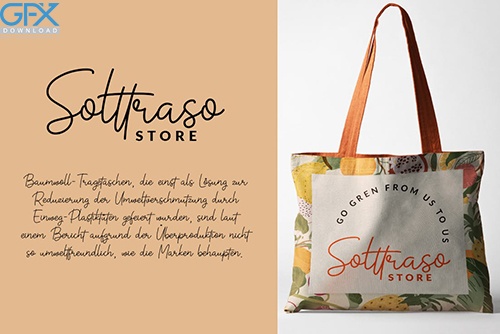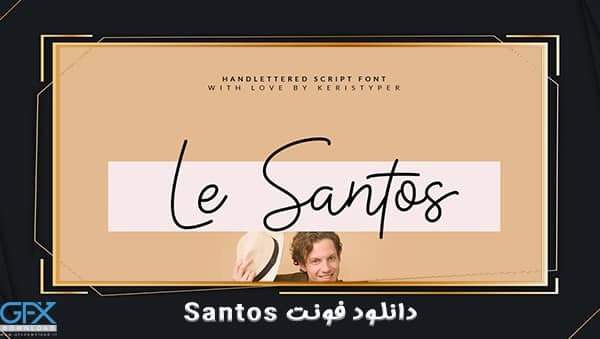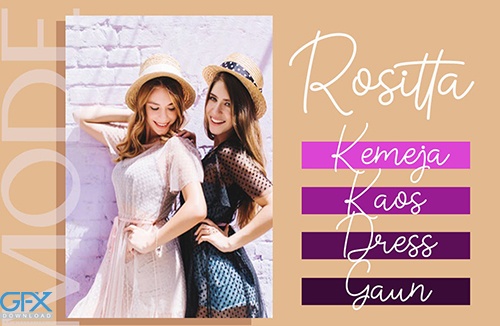
دانلود فونت رایگان دست خط Santos
فونت دست خط انگلیسی رایگان Santos
دانلود فونت دست خط انگلیسی رایگان Santos
فونت زیبا و تاثیر گذار که با ترکیب منحصر به فرد هر کاراکتر ایجاد شده است. این فونت کاملا واقعی به نظر می رسد و می تواند برای همه نیازهای پروژه شما استفاده شود. این فونت را می توان در هر زمان و در هر پروژه ای استفاده کرد. دانلود فونت رایگان دست خط Santos با پشتیبانی چند زبانه: آفریقایی ، آلبانیایی ، کاتالان ، دانمارکی ، هلندی ، انگلیسی ، استونیایی ، فرانسوی ، فنلاندی ، آلمانی ، ایسلندی ، اندونزیایی ، ایتالیایی ، مالایی ، نروژی ، پرتغالی ، اسپانیایی ، سوئدی ، زولو ، و بسیاری موارد دیگر می باشد.
فونت دست خط انگلیسی Santos
دانلود رایگان فونت دست خط Santos